尘封半世纪的神秘字体,“印研宋七”字体首发
上海印刷技术研究所17日在中国近现代新闻出版博物馆举行“非遗手工字体宋七”发布会,尘封半个世纪的“印研宋七”字体正式发布。
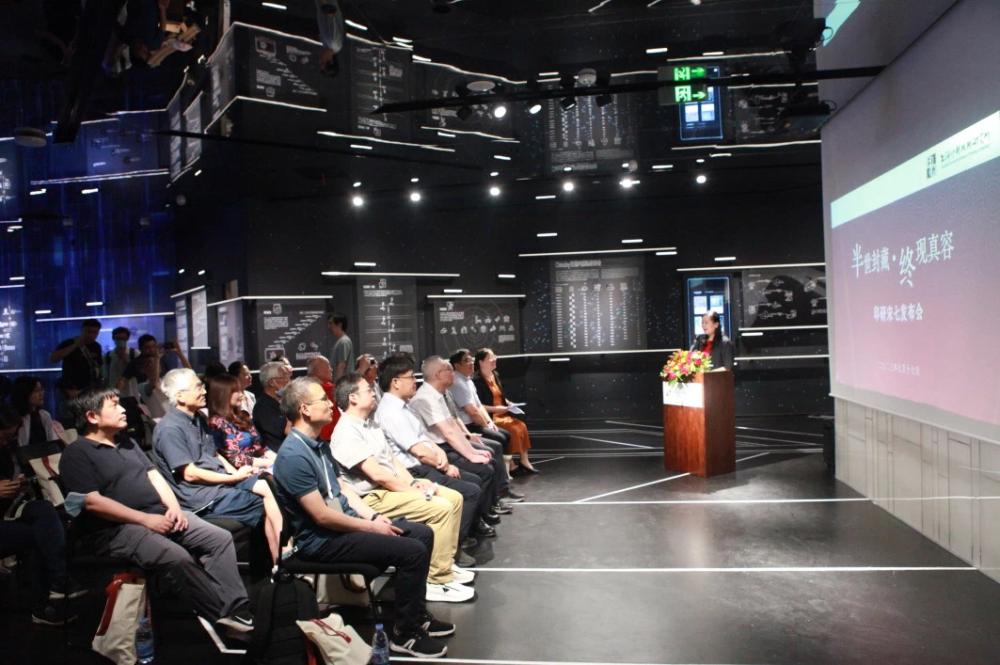
“宋七体”设计灵感来源于《康熙字典》的字头字,故也被称为康熙字典体,极具古雅风韵。有别于传统宋体字横平竖直的挺拔硬朗,“宋七体”字形修长,笔形圆润浑厚,且具有强烈的版刻风格,笔势上呈现左低右高的态势,竖弯钩委婉和顺,点的收笔处带有明显垂露感,既有楷体书写时的书法韵味,又彰显了宋体的笔意特征。其设计兼顾了美观性与实用性,不仅适用于各类书籍、报纸杂志的正文排列,同时适应时代需求,是一款可用于数字媒体屏幕显示的字体。
中华人民共和国成立初期,我国印刷铅字仍沿用旧字形字体,字体、字形杂乱,异体、变体混合使用,严重影响印刷质量和阅读效果。1959年,文化部召开会议指导上海率先进行“印刷字体改革”,以上海印刷技术研究所为基地,集聚了沪上美术创意有功力、书写正楷有造诣、雕刻字模有经验的三股人才,成立了50多人组成的字体研究室。
上海印刷技术研究所字体研究室的设计人员耗时5年,研发了一套完整的手工技艺,相继完成了“宋、黑、楷、仿”四种常用印刷字体的创写设计,总计8万字,这些字体沿用至今,不仅为新中国推广简化字和汉字使用的规范化作出了巨大贡献,也为汉字文化的普及、传承、发展起到了关键作用。2009年由上海印刷技术研究所申报的“汉字印刷字体书写技艺”项目,被列入第二批上海市非物质文化遗产项目名录。
在“宋、黑、楷、仿”四种经典印刷字体中,宋体是最常用的出版印刷字体。上海印刷技术研究所在20世纪手工设计推出了多套风格各异的宋体字,这些字体都以数字命名,每一款都承载着重大的历史使命。
其中,“宋一体”是1962年专门设计用于新中国首部《辞海》的正文用字,其字形方正,笔形清秀;结构严谨,行款整齐,阅读流畅。此后又用于1985年版《汉语大字典》等大型工具书正文。
“宋二体”是1963年为首版横排简体《毛泽东选集》正文用字而设计,后又被称为“经典著作体”,其字形继承了横轻垂重、有棱有角的传统,字形挺拔秀逸,大气疏朗,流畅自然。“宋二体”广泛用于排印各类书刊,是当今世界上应用最广的一种汉字字体。现在电脑字库里常用的书宋体,大都在该字体的基础上加工制作而成。
“宋三体”是1964年为排印《毛泽东诗词》而设计,所以又称“毛泽东诗词体”。
“宋五体”和“宋六体”分别是1970年和1980年设计的行头宋和标题宋,被广泛用于户外标语和书报杂志的标题用字。
在这些宋体的家族中有一款特殊的字体,原名“宋四体”,后改名为“宋七体”,由“汉字印刷字体书写技艺”非遗第一代传承人徐学成于1968年设计。由于历史原因,这款字体设计完成后未能问世,字稿被封存遗忘在印研所字体仓库。
2020年,在“汉字印刷字体书写技艺”非遗项目第二代传承人陈其瑞的推荐和引导下,这套字稿才被找到并重新面世。上海印刷技术研究所启动“宋七体开发”项目,由第四代非遗传承人领衔,根据手绘原稿归纳、提炼、再设计。目前,“宋七体”已完成一期开发,此次首发6763个汉字的字库产品,后续将有支持大字符集的产品面世。
上海印刷技术研究所成立于1956年,是中国现代汉字印刷字体的发源地,“宋、黑、楷、仿”等汉字印刷字体的原始创写者,也是上海市非物质文化遗产项目“汉字印刷字体书写技艺”的传承保护单位。在中国近现代新闻出版博物馆四楼艺术设计馆第一部分“汉字与出版”的“文字改革与‘整旧创新’”单元,陈列有印研所提供的“宋二体、黑二体印刷活字设计稿”。馆内导视、展板文字、雕塑设计等多处选用了印研所授权字体。其中广场雕塑“行路”使用“宋黑体”;导视馆名使用“宋二体”;主题馆二级标题、内容文字,三级标题,门牌地址等处成为“宋七体”发布前的首个用户。见证过中国新闻出版发展历程的印刷字体设计经典,正在这座全新的新闻出版专业博物馆里展示独特魅力。